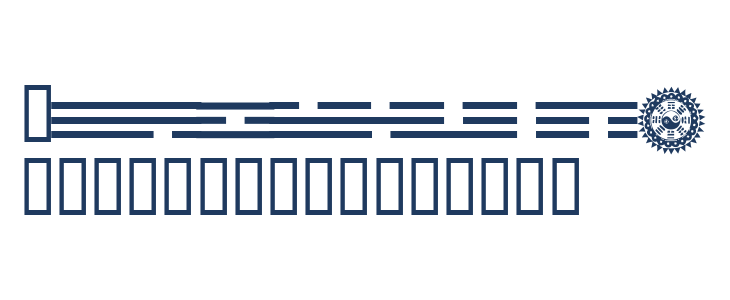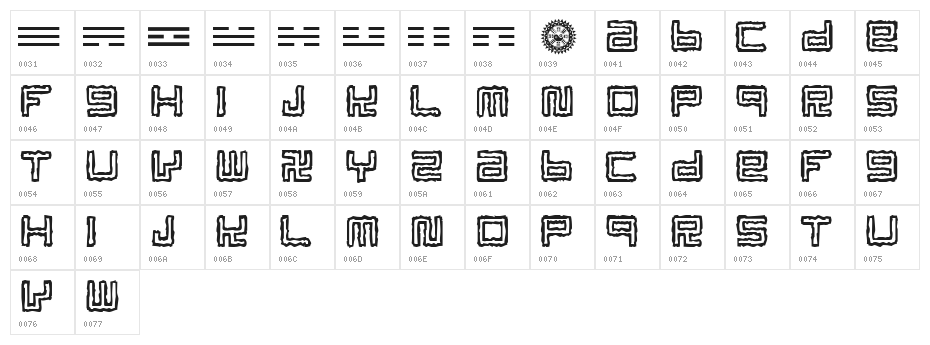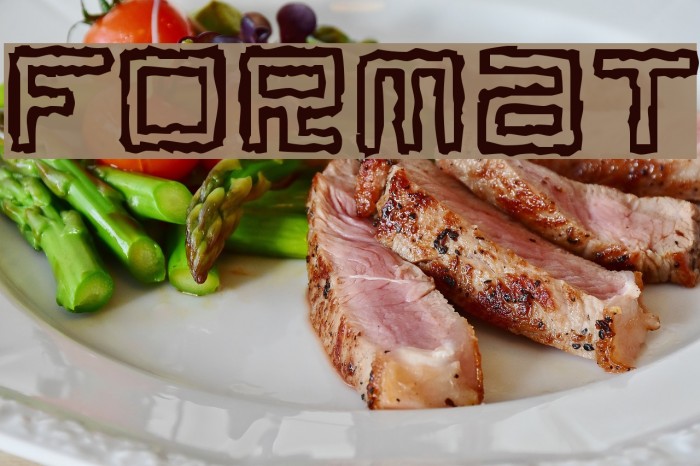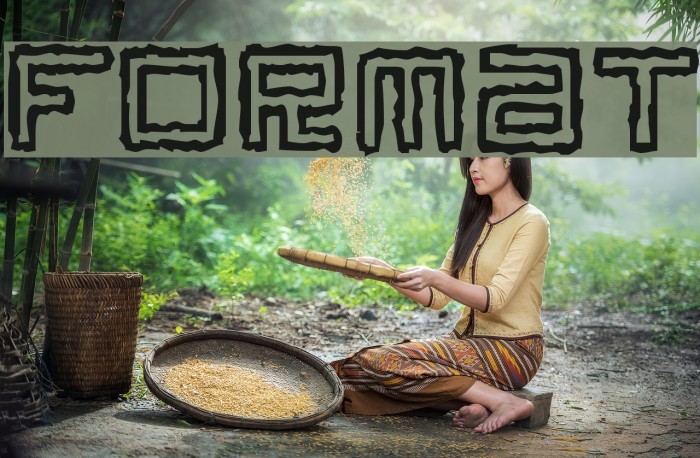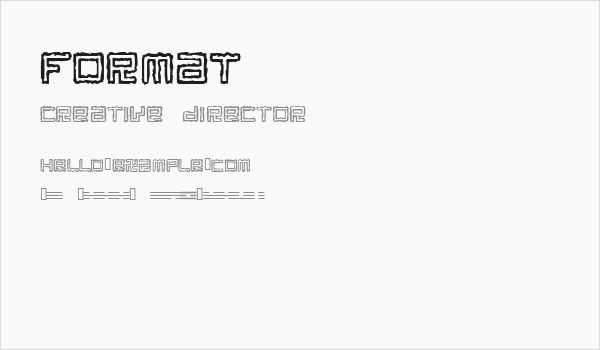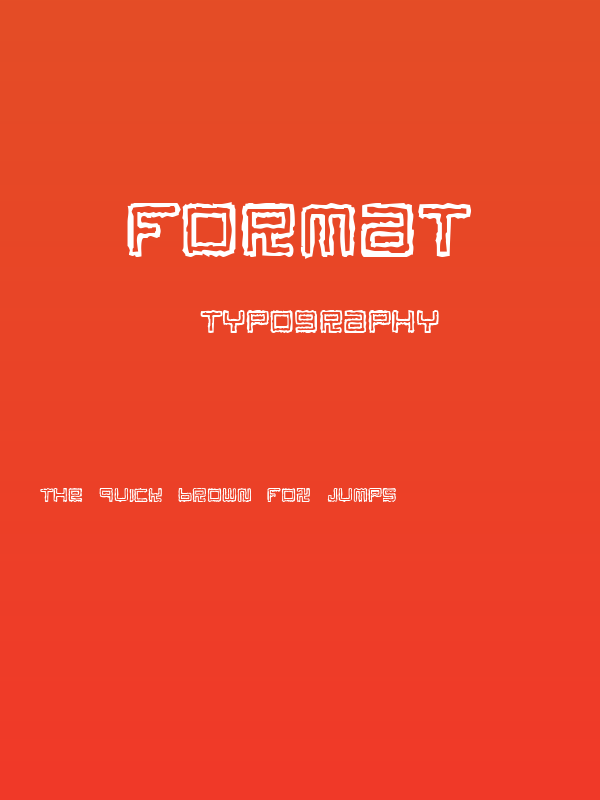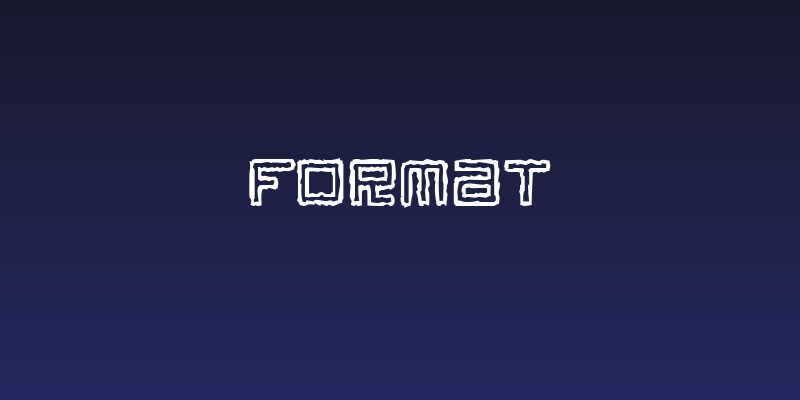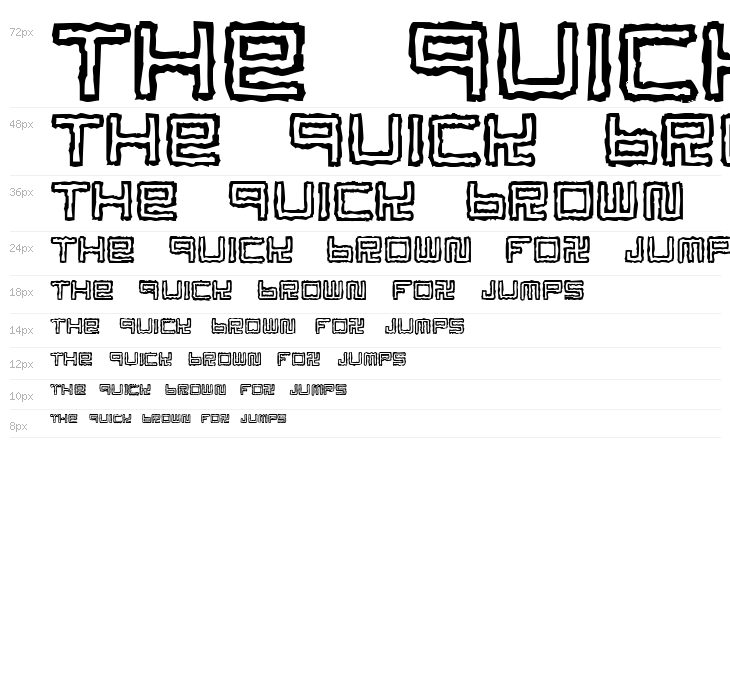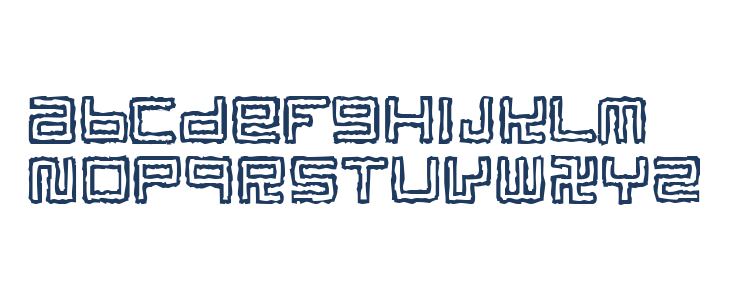
Format Font
| Progetti proposti | Ideal for creative projects such as posters, album covers, and branding materials that require a bold, artistic touch. |